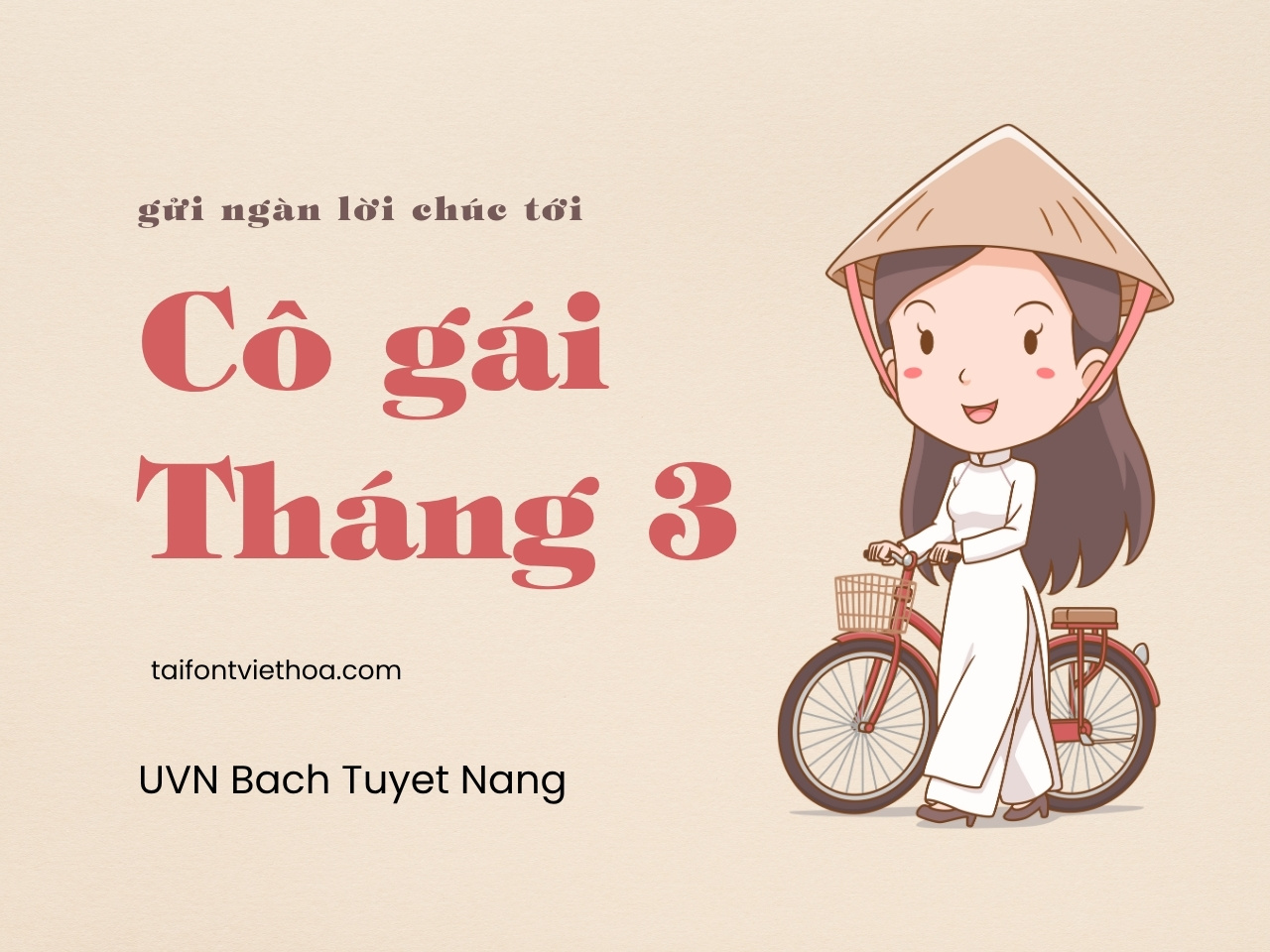
Giới thiệu về font UVN Bach Tuyet Nang
UVN Bach Tuyet Nang là phiên bản đậm của bộ font UVN Bach Tuyet, mang đậm phong cách serif cổ điển nhưng vẫn giữ được sự mềm mại, uyển chuyển đặc trưng. Font gợi cảm giác cổ tích, nhẹ nhàng và sang trọng, rất phù hợp với những thiết kế mang tính nghệ thuật cao hoặc cần tạo điểm nhấn trang trọng. Bộ font được sưu tầm và chia sẻ bởi thành viên của Font Chuẩn, đồng thời đã được taifontviethoa.com chọn lọc và ứng dụng thực tế trong các thiết kế in ấn, sự kiện và thương hiệu truyền thống.
Đặc điểm thiết kế và ứng dụng của UVN Bach Tuyet Nang
Với thân chữ đậm, chân chữ rõ ràng và cấu trúc hài hòa, UVN Bach Tuyet Nang giúp tạo ra điểm nhấn mạnh mẽ trong tiêu đề và các thành phần quan trọng của thiết kế. Độ đậm vừa phải giúp font giữ được tính dễ đọc và tính thẩm mỹ cao. Các nét bo cong tinh tế mang đến cảm giác bay bổng, dịu dàng nhưng không thiếu phần nổi bật.
Font thích hợp cho các dự án như bìa sách cổ tích, thiệp cưới, poster sự kiện văn hóa, thương hiệu mỹ phẩm, hoặc bao bì sản phẩm cao cấp. Ngành nghề phù hợp gồm: thời trang, mỹ phẩm, cưới hỏi, xuất bản nghệ thuật, giáo dục truyền thống và truyền thông văn hóa.